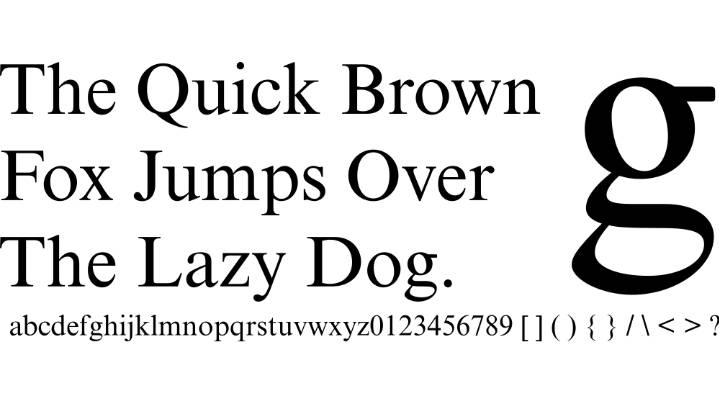
Font adalah bagian kecil dari dunia desain yang sering kita abaikan, padahal perannya sangat besar. Salah satu font yang mungkin paling sering kita temui adalah Times New Roman. Dari tugas kuliah, dokumen resmi, hingga naskah berita, font ini seperti hadir di mana-mana. Tak heran, font Times New Roman jadi salah satu tipografi paling legendaris.
5 Fakta Font Times New Roman, Awalnya untuk Surat Kabar
Times New Roman diciptakan khusus untuk surat kabar The Times pada tahun 1932
Font ini terkenal karena efisiensi ruang dan sering dipakai di dokumen resmi serta karya akademik
Dibuat dengan sentuhan seni klasik, meskipun dianggap membosankan, font ini tetap abadi dan menjadi fondasi kuat untuk teks
Meski begitu, tidak banyak orang tahu cerita unik di balik Times New Roman. Ia bukan sekadar huruf standar yang muncul otomatis di aplikasi pengolah kata, tetapi ada sejarah, tujuan khusus, dan perjalanan panjang yang membuat font ini bisa bertahan hingga sekarang. Yuk, intip lima fakta unik tentang font Times New Roman yang mungkin belum pernah kamu dengar sebelumnya!
1. Dibuat khusus untuk surat kabar The Times
Surat kabar The Times (commons.wikimedia.org/Marco Almbauer) Times New Roman pertama kali diciptakan untuk kebutuhan surat kabar, bukan untuk dokumen resmi. Stanley Morison, penasihat tipografi dari Monotype Corporation, sejak akhir 1920-an memang mengkritik huruf yang digunakan The Times karena dianggap kurang jelas dibaca. Kritik itu berbuah nyata pada tahun 1931 ketika redaksi meminta Morison merancang huruf baru yang lebih efisien. Untuk mewujudkannya, ia menggandeng Victor Lardent, seniman huruf di departemen periklanan The Times, yang kemudian menggambar bentuk visual sesuai arahan Morison.
Hasil kerja sama tersebut melahirkan desain yang ringkas sekaligus nyaman dibaca. Times New Roman akhirnya dipakai pertama kali di halaman The Times pada 3 Oktober 1932 dan langsung mendapat perhatian. Kombinasi kejelasan, efisiensi ruang, dan sentuhan estetika klasik membuatnya cepat populer di dunia penerbitan. Dari sana, font ini terus menyebar hingga menjadi standar global seperti yang kita kenal sekarang.
2. Terkenal karena efisiensi ruang
Ilustrasi Times New Roman font (commons.wikimedia.org/TIMES) Salah satu keunggulan utama Times New Roman adalah bentuk hurufnya yang ramping. Desainnya memungkinkan lebih banyak teks masuk dalam satu halaman tanpa mengurangi kenyamanan membaca. Hal ini sangat penting bagi surat kabar yang harus memuat artikel panjang dengan ruang terbatas.
Efisiensi tersebut pula yang membuatnya sering dipakai di dokumen resmi dan karya akademik. Mahasiswa mungkin sering “berdosa” dengan memanfaatkan font lain agar halaman terlihat lebih panjang. Tapi dengan Times New Roman, teks terlihat ringkas dan rapi.
3. Pernah jadi font wajib di banyak dokumen resmi
Tangkapan layar teks skripsi (Dok. pribadi/Julita Puspita) Bagi banyak orang, Times New Roman identik dengan tugas sekolah atau skripsi. Memang benar, selama bertahun-tahun font ini ditetapkan sebagai standar resmi di banyak institusi. Alasannya sederhana, yakni font ini formal, mudah dibaca, dan terkesan profesional.
Beberapa lembaga pemerintah hingga universitas masih mensyaratkan penggunaan Times New Roman. Bahkan ada yang menetapkan ukuran tertentu seperti 12 pt dengan spasi ganda sebagai aturan baku. Walaupun banyak font modern bermunculan, aura formal Times New Roman masih sulit digantikan. Ia seperti setelan jas klasik yang tak pernah ketinggalan zaman.
4. Dibuat dengan sentuhan seni klasik
Plantin font (commons.wikimedia.org/Flamon) Times New Roman mungkin terlihat sederhana, tetapi jejaknya berakar pada tradisi seni klasik. Tipografi ini dikembangkan dari font Monotype bernama Plantin, yang diciptakan pada awal abad ke-20 dengan meniru gaya huruf Robert Granjon di era Renaisans. Dari dasar klasik itulah, Stanley Morison mengembangkannya agar sesuai dengan kebutuhan media cetak modern.
Meskipun mirip dengan Plantin, Times New Roman hadir dengan sentuhan berbeda yang membuatnya unik. Kontras antara goresan tipis dan tebal diperkuat, sehingga huruf-hurufnya tampak lebih tajam dan jelas di kertas. Keunggulan ini menjadikannya tidak hanya elegan secara visual, tapi juga sangat fungsional untuk menyampaikan teks panjang.
5. Sering dianggap membosankan tapi tetap abadi
Times New Roman sample (commons.wikimedia.org/Atanamir) Menariknya, meski banyak dipakai, font Times New Roman sering dicap membosankan. Banyak yang merasa font ini terlalu biasa, terlalu aman, dan kurang ekspresif. Namun justru karena “sifat aman”-nya itu, font ini bisa bertahan dan dipakai di mana-mana. Ia menjadi pilihan netral yang jarang salah tempat.
Bahkan, status “membosankan” ini membuatnya unik. Times New Roman tidak berusaha menonjol, tapi malah jadi fondasi yang kuat untuk teks. Ia mungkin bukan bintang panggung, tapi selalu ada di balik layar sebagai pendukung utama. Inilah alasan mengapa Times New Roman tetap abadi, meski banyak font baru bermunculan.
Times New Roman bukan hanya sekadar huruf yang muncul default di komputer. Ia adalah bagian dari sejarah tipografi yang berhasil menjembatani kebutuhan praktis dan nilai estetika. Dari surat kabar hingga dokumen resmi, font ini sudah menemani jutaan tulisan. Jadi, setiap kali kamu mengetik dengan Times New Roman, ingatlah bahwa ada sejarah panjang dan filosofi menarik di balik setiap hurufnya.